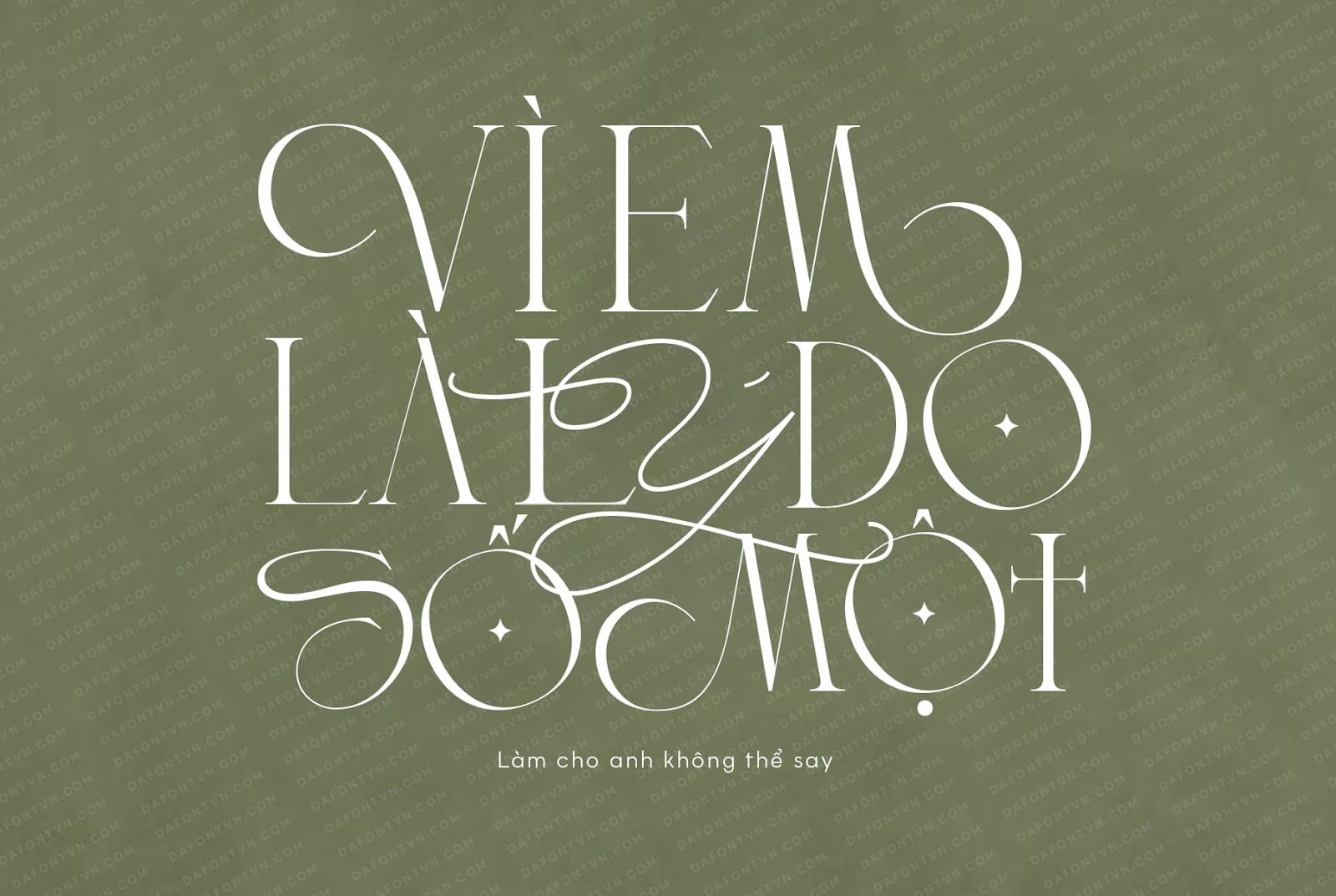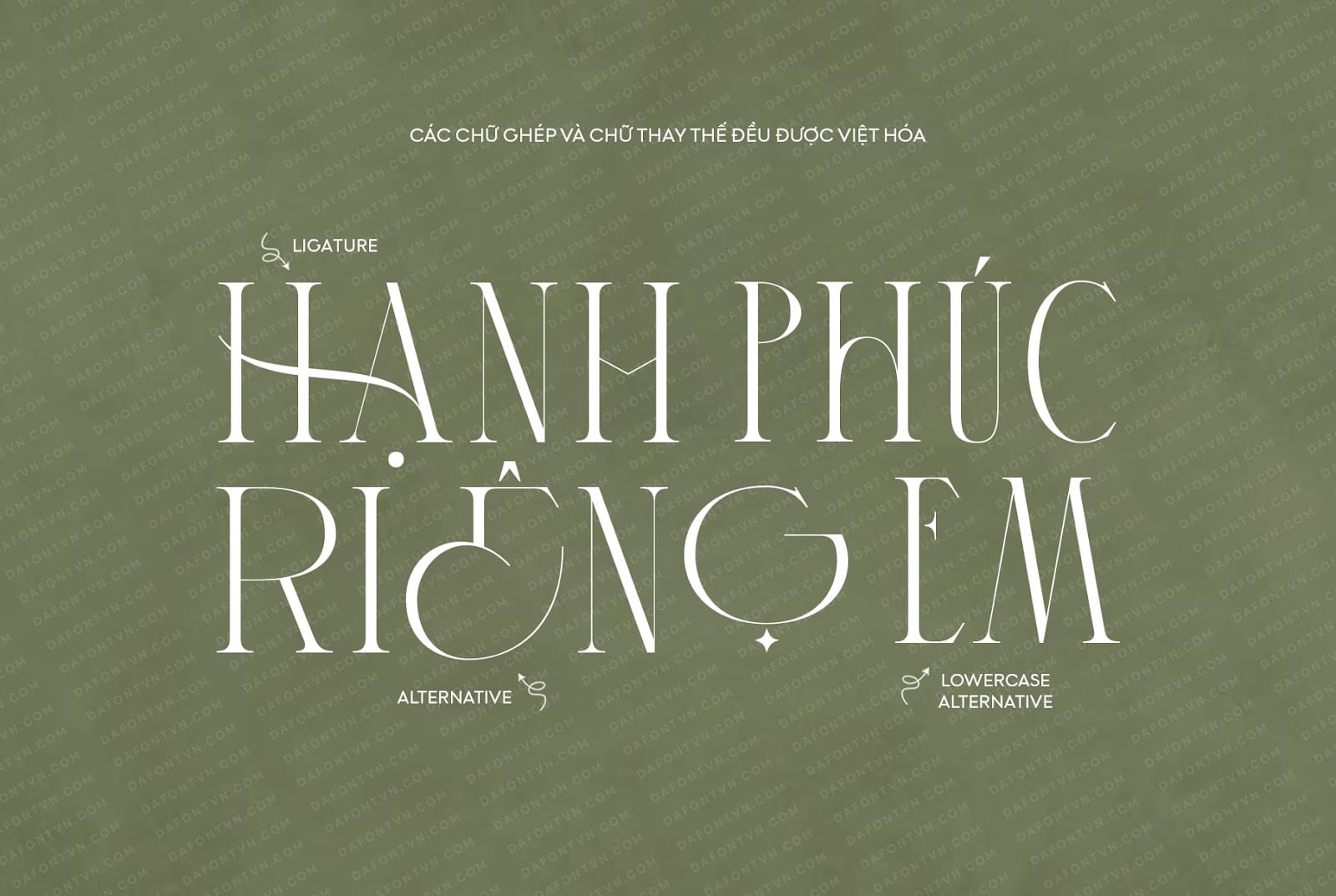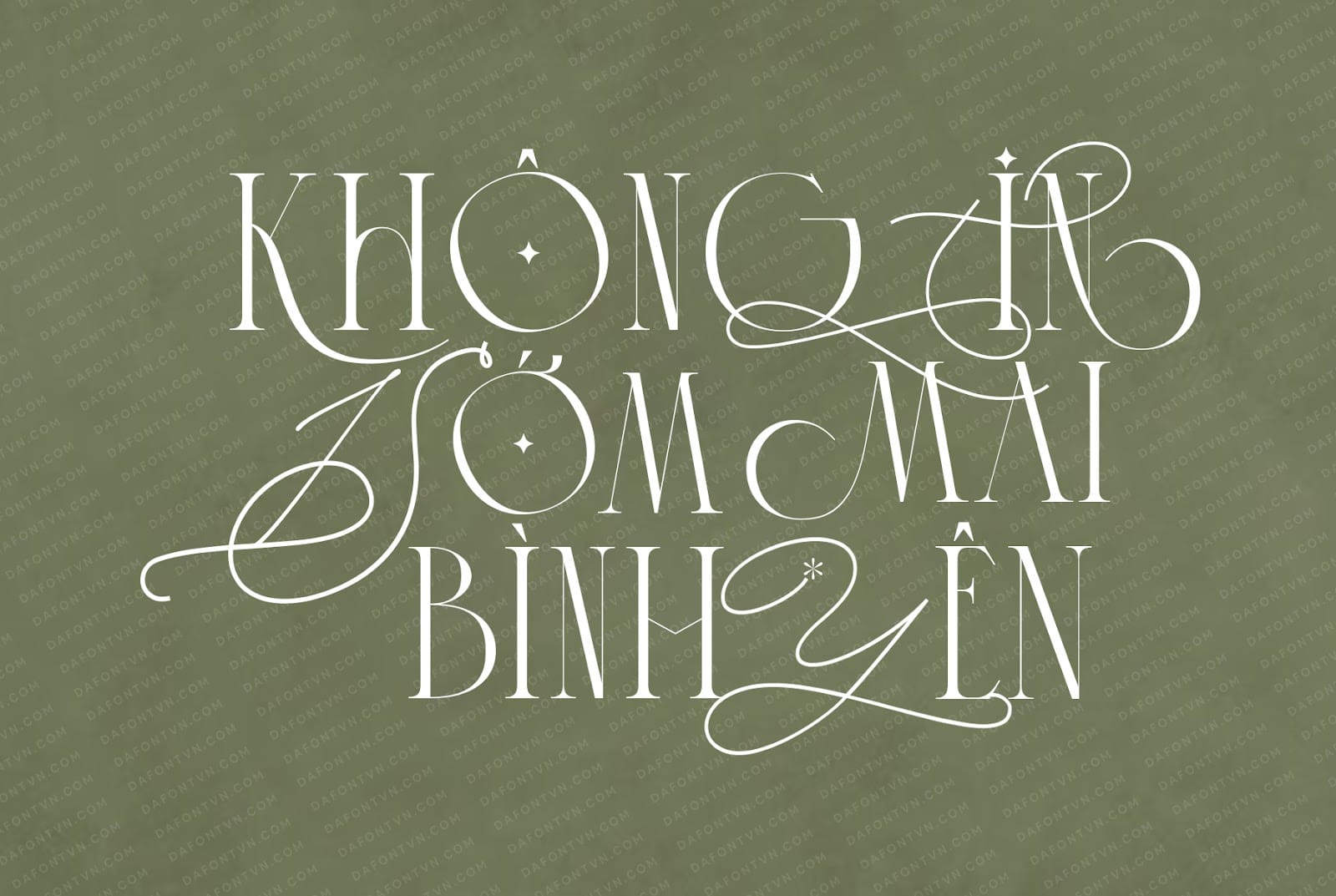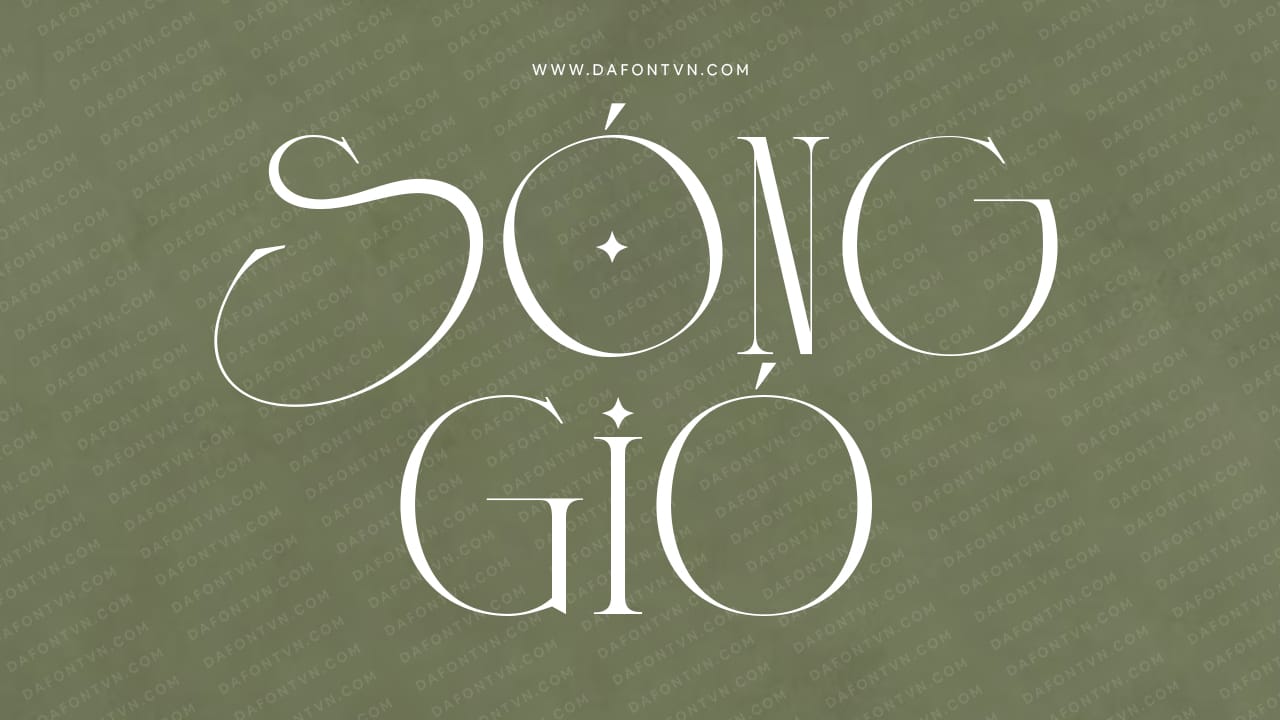
Supremely Luxurious là một font chữ serif tinh tế và quyến rũ. Những đường cong duyên dáng và đường nét sang trọng của nó sẽ làm tăng thêm nét tinh tế cho các tác phẩm của bạn.
Các đường nét rõ ràng của font Supremely Luxurious được cân bằng bởi những chi tiết phức tạp tinh tế giúp bộc lộ đặc điểm của nó và khiến nó trở nên nổi bật khi sử dụng trong bất kỳ thiết kế nào. Kiểu chữ này không chỉ quyến rũ về mặt thị giác mà còn hứa hẹn tính linh hoạt trong ứng dụng.
Mỗi chữ cái đều được chế tạo cẩn thận đến mức hoàn hảo, đảm bảo kết quả liền mạch và hấp dẫn về mặt thị giác. Với các chi tiết phức tạp của phông chữ này khiến nó nổi bật so với các phông chữ còn lại, khiến nó trở thành một sự bổ sung thực sự độc đáo cho bất kỳ bộ sưu tập font chữ việt hóa nào.
Cho dù đó là lời mời cao cấp hay tiêu đề của một tạp chí thời trang, Supremely Luxury luôn sẵn sàng truyền tải vào bất kỳ dự án nào một nét sang trọng.
Cho dù bạn đang thực hiện một chiến dịch thời trang cao cấp hay đang tạo một thiệp đám cưới đẹp mắt, thì Supremely Luxurious chắc chắn sẽ làm cho dự án của bạn trở nên nổi bật. Phông chữ này hoàn hảo cho mọi thiết kế như xây dựng thương hiệu, bao bì sản phẩm, thiệp mời, nhãn hiệu, tiêu đề, áp phích, tạp chí hoặc logo.
Với sự pha trộn độc đáo giữa sự hiện đại và vượt thời gian, Supremely Luxury nổi bật như một sự lựa chọn hoàn hảo cho các nhà thiết kế đang tìm cách truyền tải vẻ độc quyền và uy tín cho tác phẩm của họ.
Ngoài ra, Supremely Luxurious bao gồm hơn 500 chữ ghép (Ligature) và chữ cái thay thế (Alternative) giúp bạn có thể dễ dàng kết hợp để tạo ra những điểm nhấn ấn tượng hơn cho thiết kế của mình.
Tất cả các ký tự chữ ghép và chữ cái thay thế đều được việt hóa. Vì vậy bạn có thể sử dụng tính năng Opentype hoặc bảng Glyph trên PTS, AI để lựa chọn các ký tự này nhé.